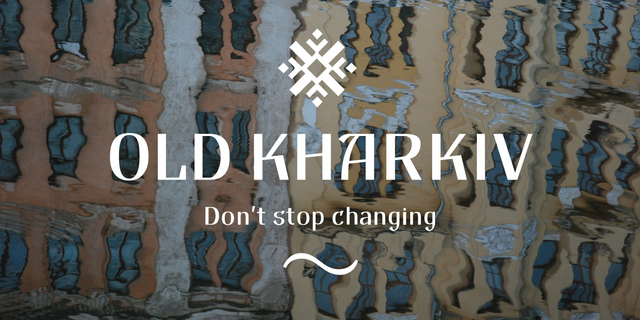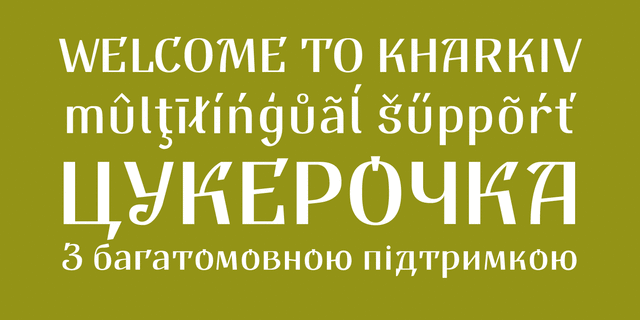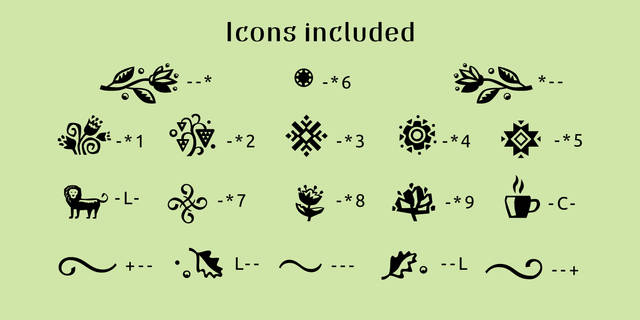
Толчком к началу работы над шрифтом «Старый Харьков» стала фотография первой половины 20 века с вывеской на здании нынешнего Харьковского национального университета искусств имени Ивана Котляревского. В процессе работы шрифт приобрел уникальные черты, которых не было на оригинальной вывеске, например, капли в крупных буквах были заменены на срезанные засечки. В этом шрифте представлены буквы всех основных европейских языков и набор основных специальных символов. Некоторые крупные буквы (там где это позволила их форма) имеют удлиненные декоративные элементы (росчерки) чтобы использовать их в качестве буквицы. Для некоторых украинских букв (Щ, Ц, Л, С, Ж) созданы стилистические альтернативы. Также в виде бонуса шрифт содержит до десятка графических элементов, которые можно использовать в тексте. Шрифт разработан Богданом Гдалем в 2016-2017 году.